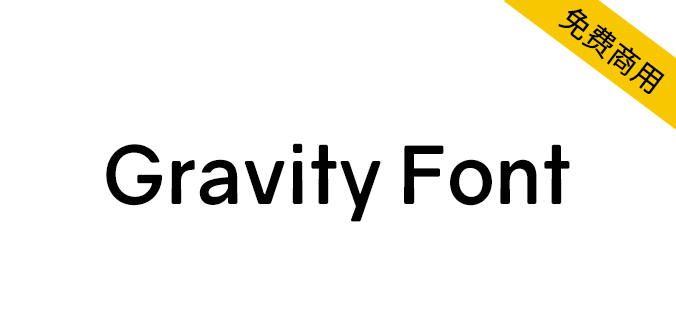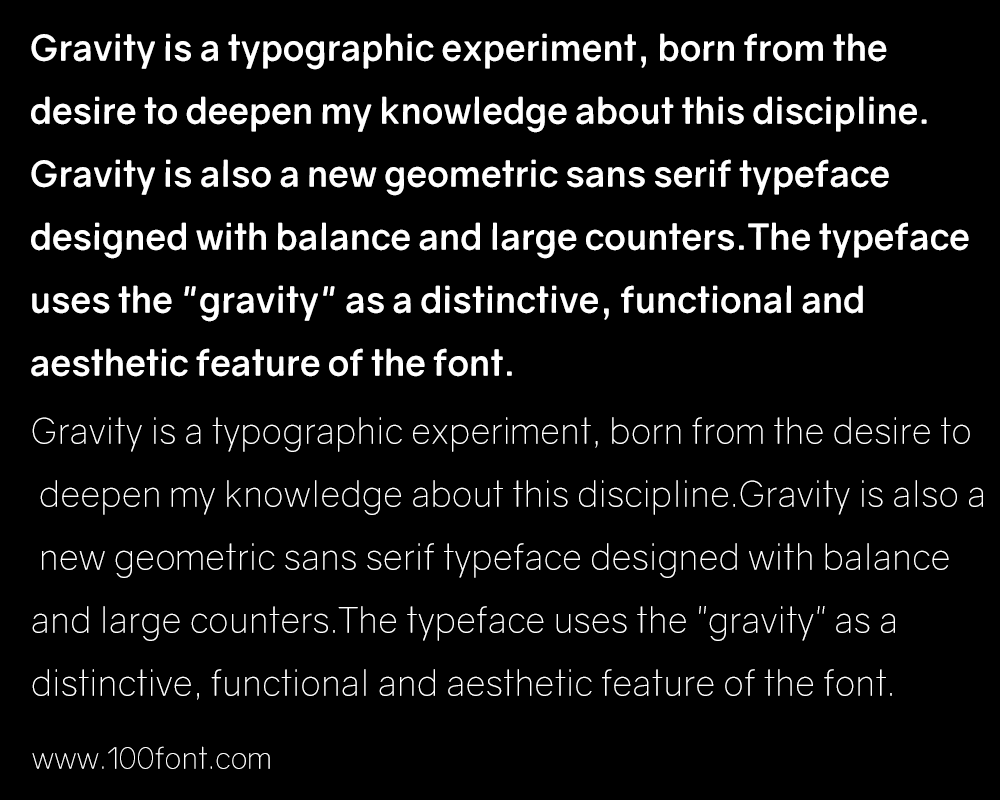
Gravity 是一个排版实验,源于加深我对这门学科知识的渴望。Gravity 也是一种新的几何无衬线字体,设计有平衡和大计数器。该字体使用“重力”作为字体的独特、功能和美学特征。它将被“Accademia di Belle Arti Palermo”用作官方字体。Gravity 也是我的第一个字体。希望你喜欢!如果您想尝试,请免费下载。
Gravity is a typographic experiment, born from the desire to deepen my knowledge about this discipline.Gravity is also a new geometric sans serif typeface designed with balance and large counters.The typeface uses the "gravity" as a distinctive, functional and aesthetic feature of the font. It is goin to be used as official font by "Accademia di Belle Arti Palermo".
Gravity is also my first typeface. Hope you enjoy! If you want to try it, download it for free